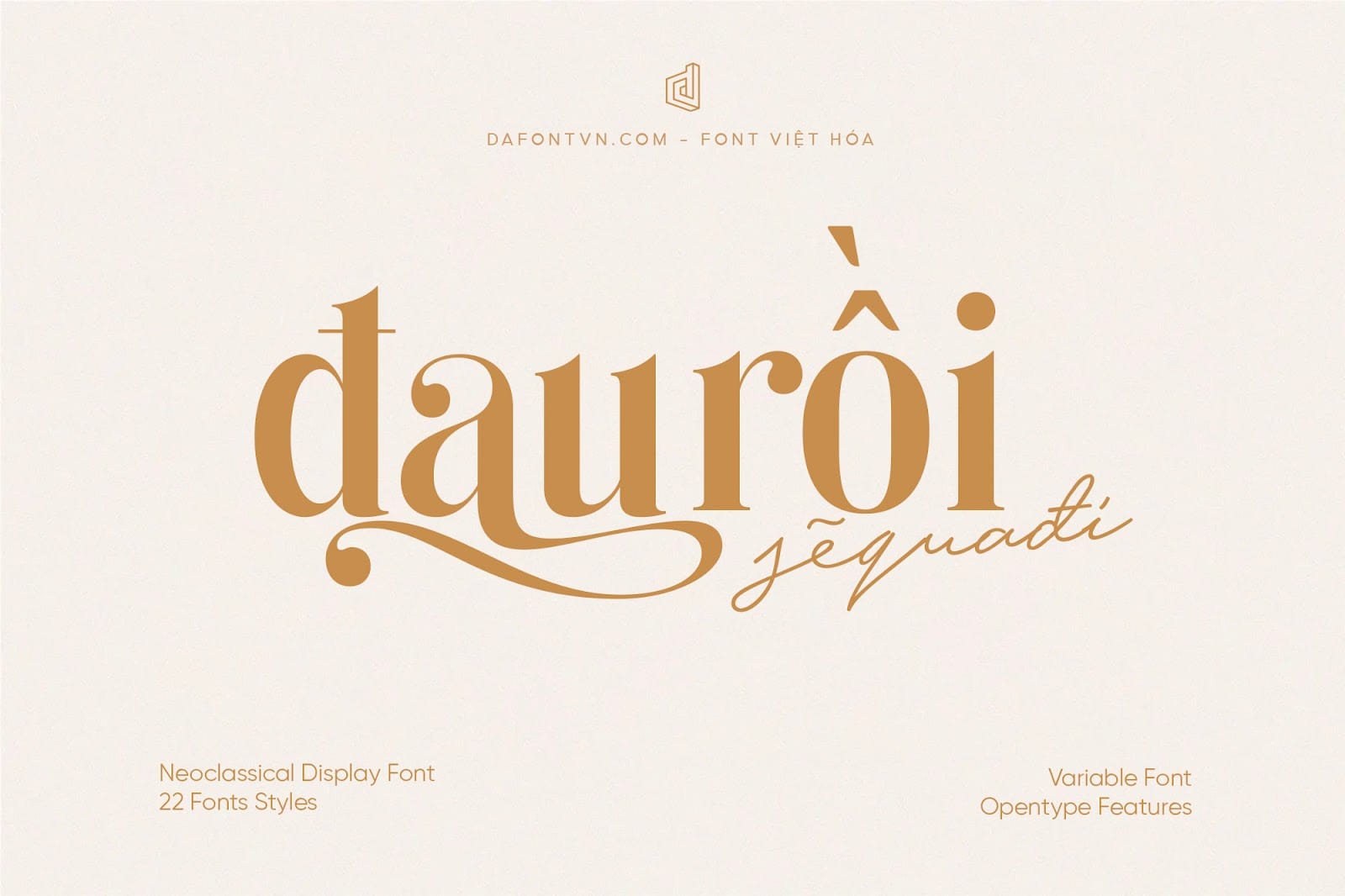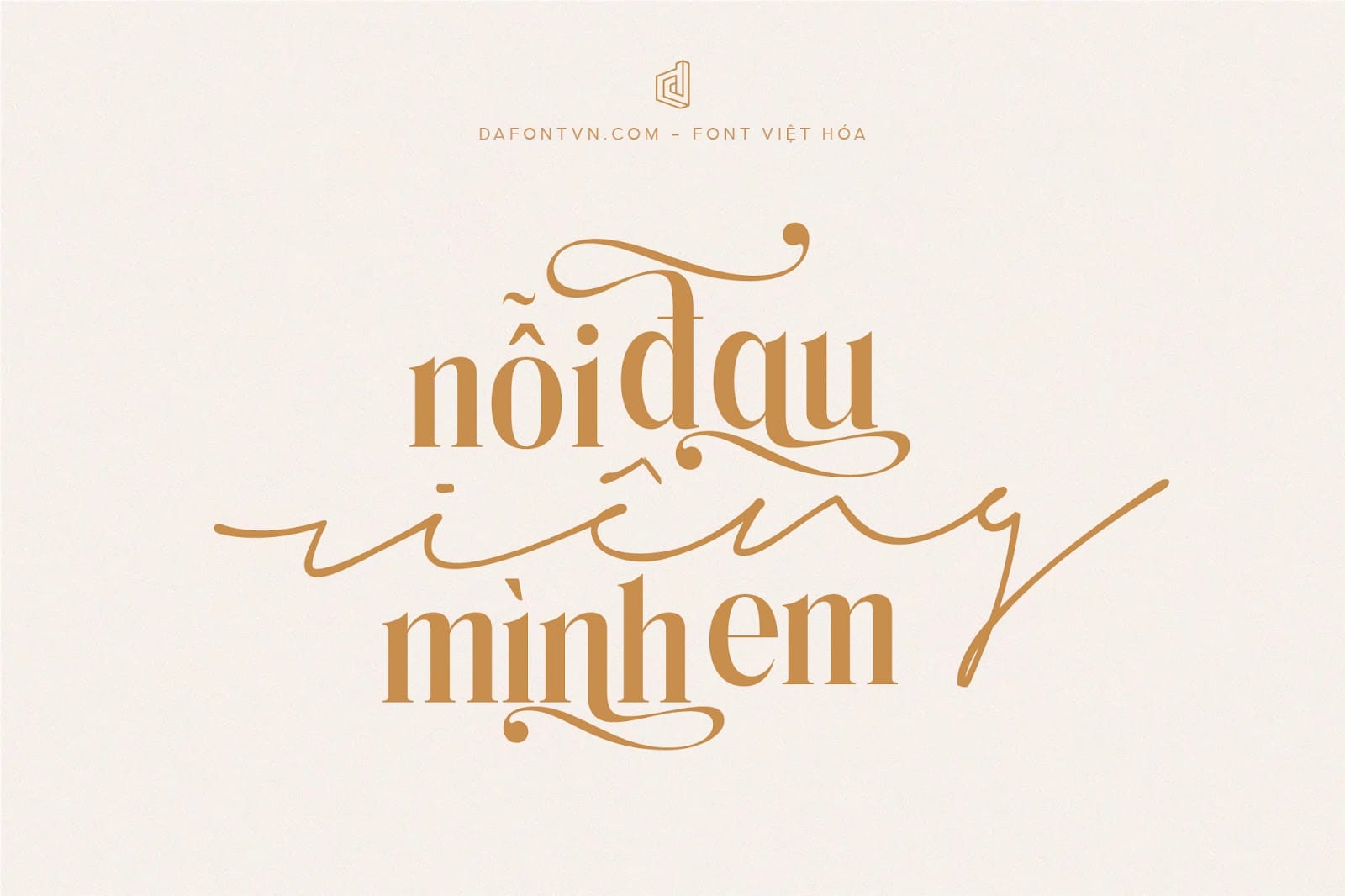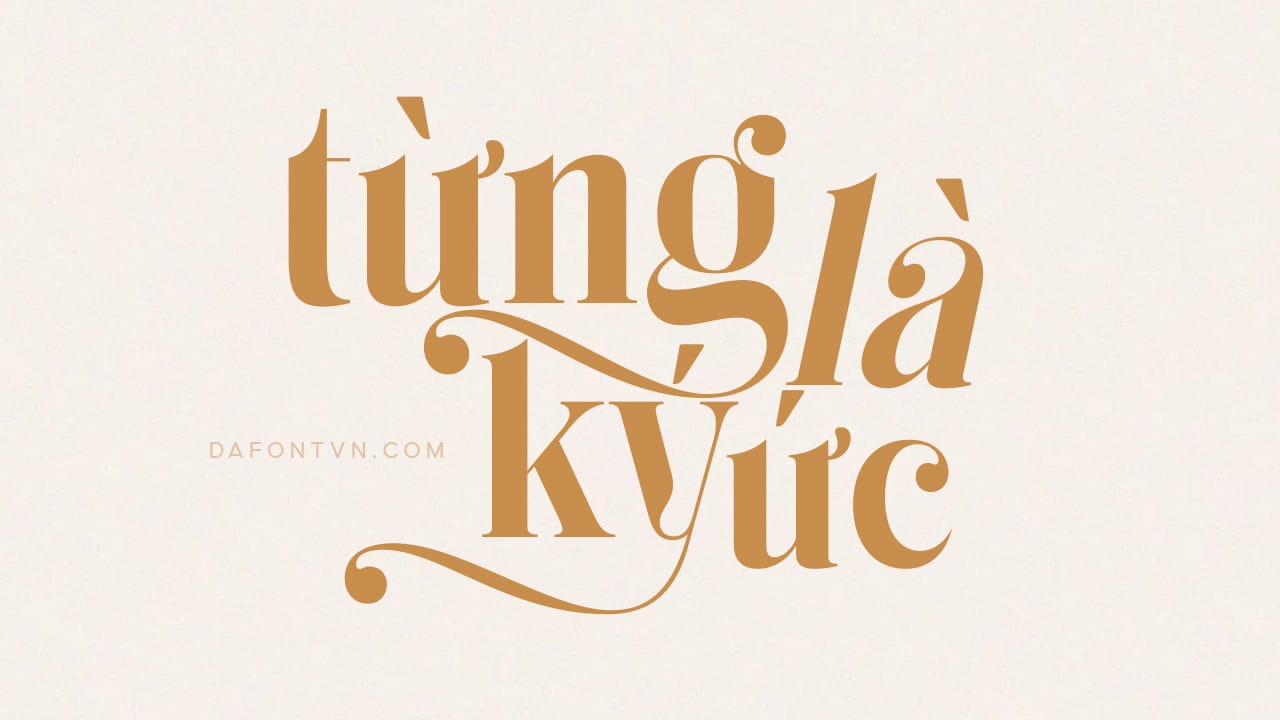
Giới thiệu Kage Pro Font Kage Pro được lấy cảm hứng từ những thiết kế vào thế kỷ 18, có sự tương phản cực kỳ hợp lý so với phong cách serif trước đó, làm cho font ấn tượng và sang trọng hơn. Kiểu font này có liên quan mật thiết đến thiết kế thời trang, đặc biệt là ở châu Âu và thậm chí còn lan rộng trên toàn cầu. Kage Pro mang đến sự mới mẻ hơn, phá cách hơn và linh hoạt trong thiết kế.
Kage Pro được thiết kế tỉ mỉ với các đường nét mượt mà phù hợp cho rất nhiều các thiết kế khác nhau như sản phẩm, thời trang, tạp chí, typography, quảng cáo… Các chuyển đổi hiện đại của mỗi kiểu chữ nhẹ nhàng hơn, vì vậy định vị lại và tăng kích thước của font chữ này, nó sẽ đẹp mà không làm ảnh hưởng các yếu tố khác.
Đặc biệt, Kage Pro Font Family có 22 kiểu trong đó có 11 kiểu upright và 11 kiểu oblique từ Thin đến Black, ấn tượng hơn là mỗi kiểu có đến 1.655 glyph vì vậy mà bạn tha hồ sáng tạo để tạo ra những thiết kế ấn tượng và hoàn hảo hơn.